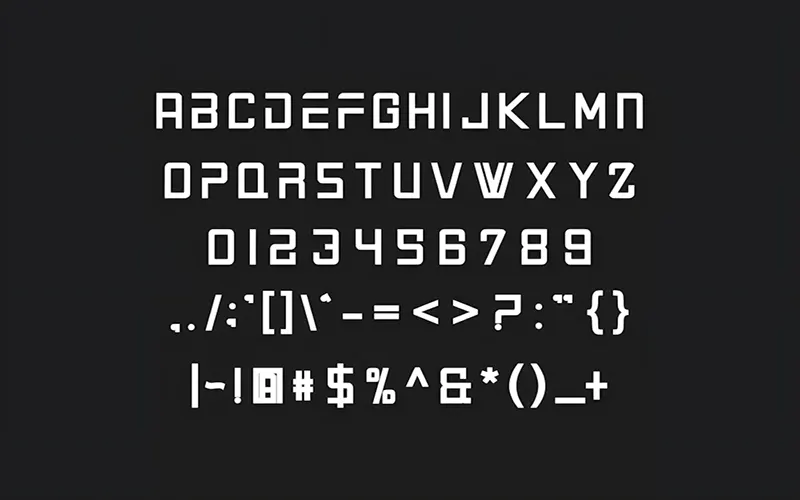
Font chữ cứng cáp là nhóm phông chữ sở hữu cấu trúc khung hình học vuông vức, đường nét dày dặn và trọng lượng chữ lớn, tạo cảm giác về sự bền vững và sức mạnh. Trong lĩnh vực bao bì, những font chữ này thường được chọn làm bộ nhận diện cho các sản phẩm công nghệ, linh kiện điện tử hoặc thiết bị công nghiệp nhờ vẻ ngoài nam tính và đáng tin cậy. Doozypack.vn cung cấp bộ font chữ cứng Việt hóa tuyển chọn, giúp bạn xây dựng hình ảnh thương hiệu vững chãi và chuyên nghiệp trên mọi ấn phẩm thiết kế.
Tại sao font chữ cứng cáp lại được ưu tiên cho các ngành công nghiệp?
Việc lựa chọn kiểu chữ cứng cáp không chỉ phục vụ mục đích thẩm mỹ mà còn mang lại những giá trị thực tế trong giao tiếp thị giác.
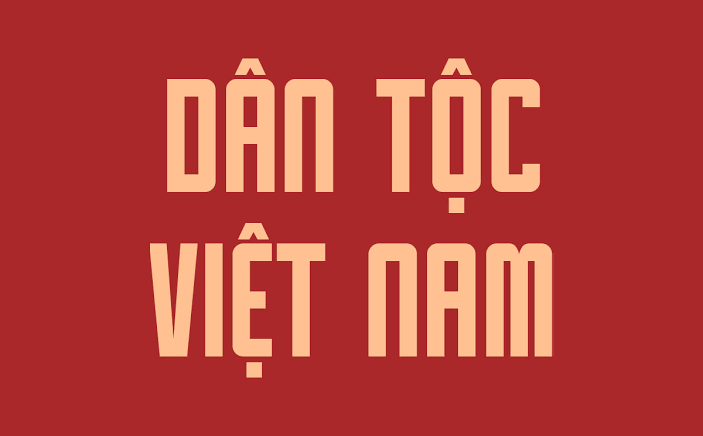
Khẳng định sự tin cậy và sức mạnh thương hiệu
Các đường nét vuông vức và dày đặc của font chữ cứng tạo ra cảm giác về một cấu trúc không thể phá vỡ. Đối với khách hàng, một bao bì sử dụng phông chữ mạnh mẽ sẽ gợi liên tưởng đến chất lượng bền bỉ của sản phẩm bên trong. Đây là yếu tố then chốt để xây dựng niềm tin cho các ngành hàng như xây dựng, cơ khí hoặc các dòng sản phẩm đồ thể thao nam giới.
Khả năng hiển thị rõ nét trên các chất liệu bao bì thô
Khác với các dòng font mảnh, font chữ cứng cáp có ưu điểm là cực kỳ dễ đọc ngay cả khi in trên các bề mặt giấy thô mộc như giấy Kraft hoặc thùng carton sóng. Nhờ diện tích bề mặt nét chữ lớn, các thông tin quan trọng như tên thương hiệu hay thông số kỹ thuật luôn hiển thị sắc nét, hạn chế tối đa hiện tượng mờ nhòe trong quá trình vận chuyển và lưu kho.
Top bộ font chữ cứng Việt hóa được các Designer săn đón
Dưới đây là một số gợi ý font cứng việt hóa được đội ngũ chuyên môn tại Doozypack.vn tin dùng cho các dự án in ấn bao bì:
- Font Bebas Neue: Một trong những bộ font All-caps (chữ in hoa) kinh điển nhất, mang lại vẻ ngoài hiện đại, sạch sẽ và vô cùng quyết đoán.
- Font Roboto Condensed: Phiên bản cô đặc giúp tiết kiệm không gian thiết kế nhưng vẫn giữ được sự chắc chắn, phù hợp cho các tem nhãn nhiều thông tin.
- Font Montserrat (Bold): Sở hữu cấu trúc hình học chuẩn mực, tạo nên sự vững chãi và chuyên nghiệp cho các thiết kế tối giản.
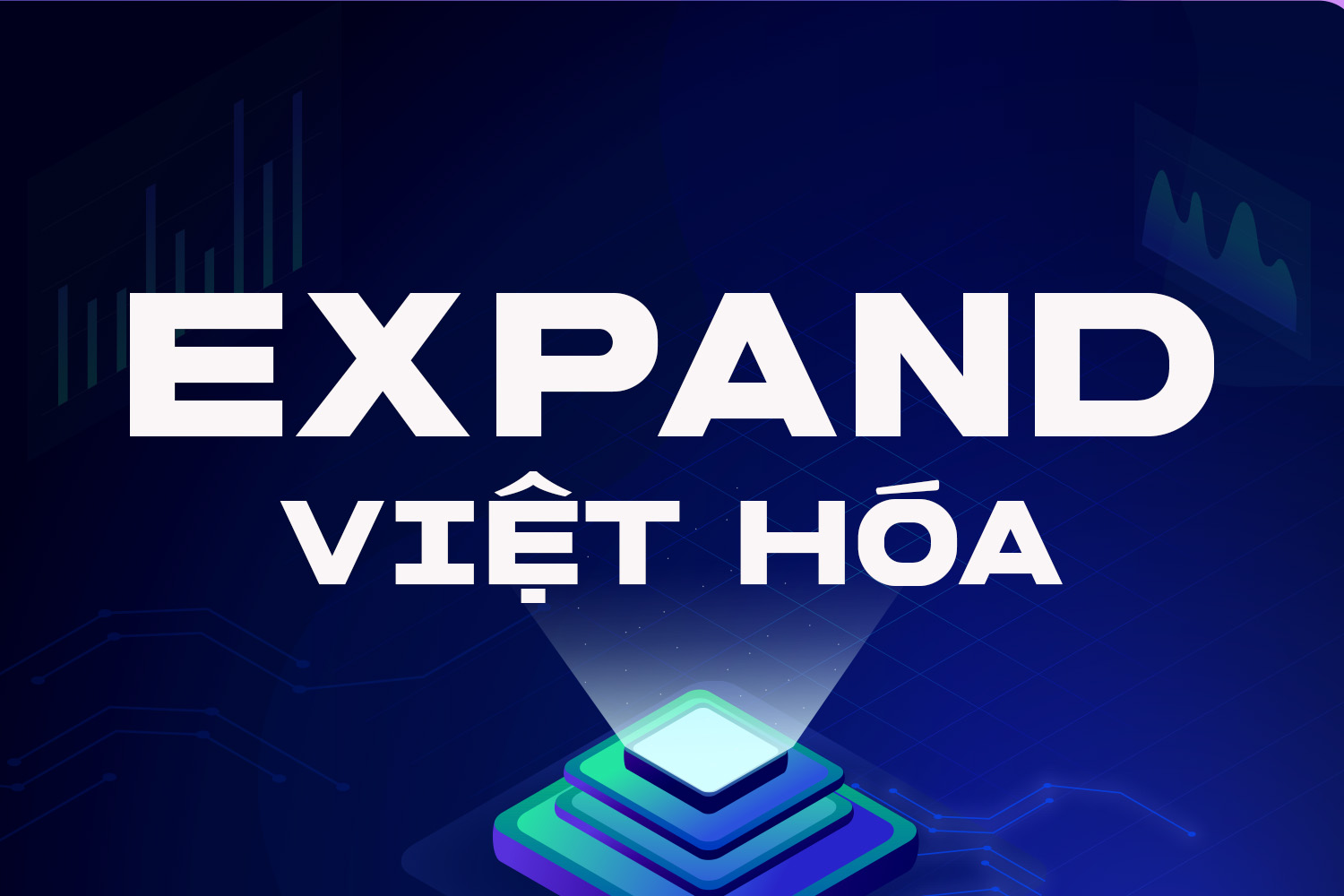
| Phong cách Font | Đặc điểm thị giác | Lĩnh vực ứng dụng |
| Geometric Sans (Hình học) | Vuông vức, hiện đại | Hộp linh kiện điện tử, túi giấy thời trang nam, logo công nghệ. |
| Condensed (Cô đặc) | Hẹp bề ngang, mạnh mẽ | Tem nhãn thông số kỹ thuật, bao bì thực phẩm đóng gói. |
| Heavy / Black (Siêu đậm) | Rất dày, nổi bật | Headline poster sự kiện thể thao, in trên thùng carton vận chuyển. |
Tư vấn từ chuyên gia: Để thiết kế bao bì không bị thô cứng, bạn nên phối hợp font chữ cứng cáp (cho tiêu đề chính) với một font không chân nét mảnh (cho nội dung phụ). Sự tương phản này giúp bản thiết kế có độ thoáng và chuyên nghiệp hơn.
03 Ứng dụng của font chữ cứng cáp trong sản xuất bao bì giấy
Tại Doozypack.vn, chúng tôi nhận thấy font chữ nét cứng mang lại hiệu quả thị giác rất tốt trên các thành phẩm thực tế:
- Hộp giấy đựng linh kiện điện tử: Các thông số mã hiệu sản phẩm được trình bày bằng font cứng giúp người dùng dễ dàng đọc được ngay cả dưới ánh sáng yếu trong kho bãi.
- Túi giấy thời trang nam: Tên thương hiệu in bằng font Bebas Neue ép kim nhũ bạc trên nền giấy đen tạo nên diện mạo vô cùng đẳng cấp và nam tính.
- Tem nhãn công nghiệp: Các ký hiệu cảnh báo hoặc tên sản phẩm in bằng phông chữ cứng đảm bảo tính rõ ràng, giúp tăng mức độ nhận diện và sự chuyên nghiệp.
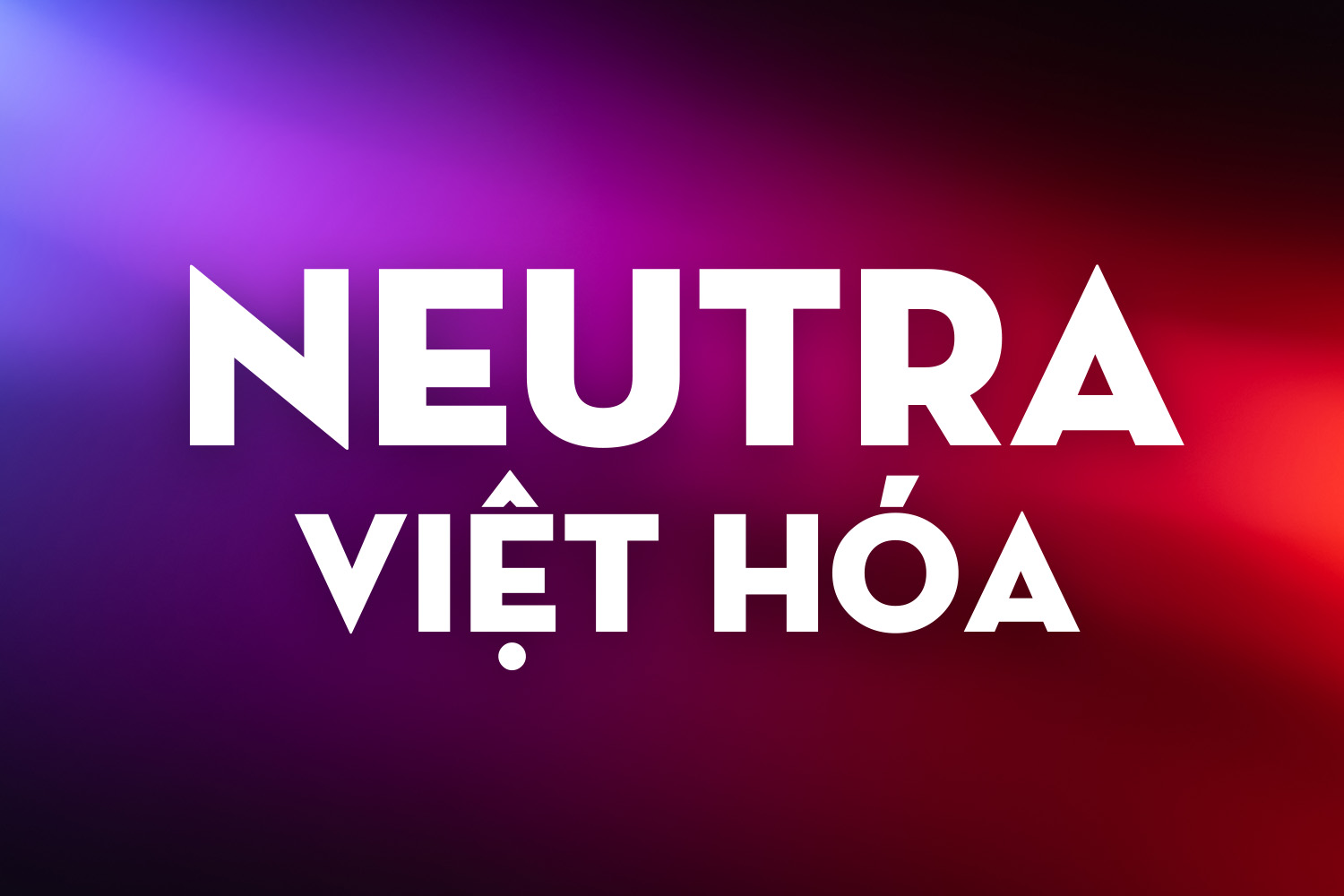
Những lưu ý kỹ thuật khi in ấn font chữ nét cứng tại Doozypack.vn
In ấn các khối chữ đậm và vuông vức cần lưu ý một số yếu tố kỹ thuật để tránh hỏng bản thiết kế khi sản xuất thực tế:
- Kỹ thuật dập nổi (Embossing): Font chữ cứng cáp là lựa chọn tuyệt vời để làm dập nổi. Các góc cạnh vuông vức giúp khuôn dập tạo ra những đường nét sắc sảo, tạo chiều sâu ấn tượng cho bao bì.